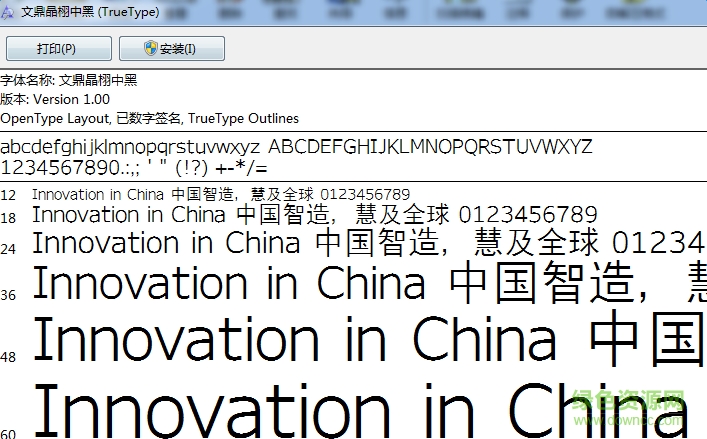
文鼎晶栩中黑bold
文鼎晶栩中黑字體是文鼎字庫開的一款應(yīng)用于設(shè)計方面的中方黑體字體,該字體非常具有個性,可廣泛應(yīng)用于平面設(shè)計、廣告設(shè)計、報紙雜志、正文標(biāo)題等領(lǐng)域,喜歡的網(wǎng)友可免費下載收藏。
文鼎晶栩中黑字體是一款非常具有個性的字體,該字體線條非常優(yōu)雅,有需要的朋友可以來綠色資源網(wǎng)下載使用!